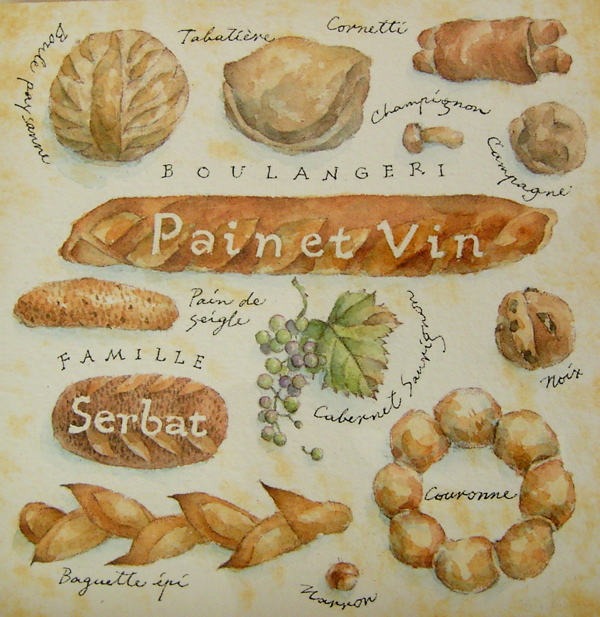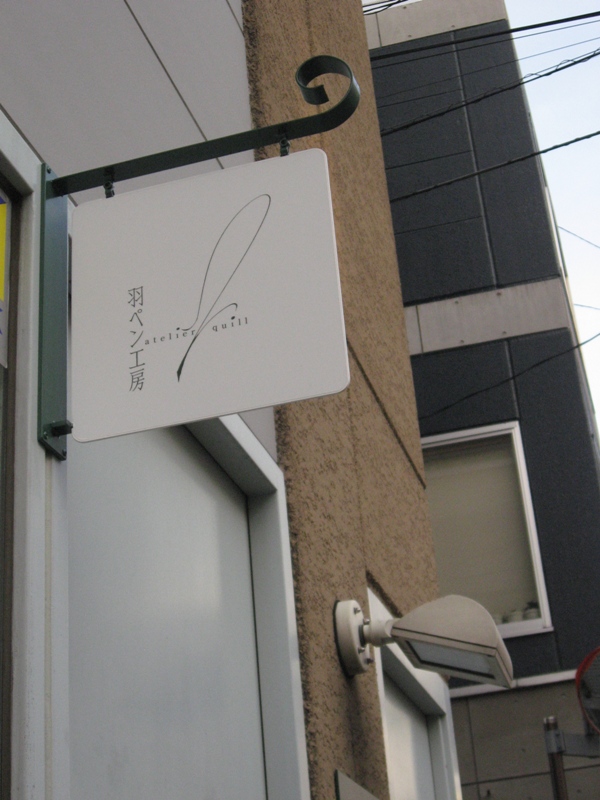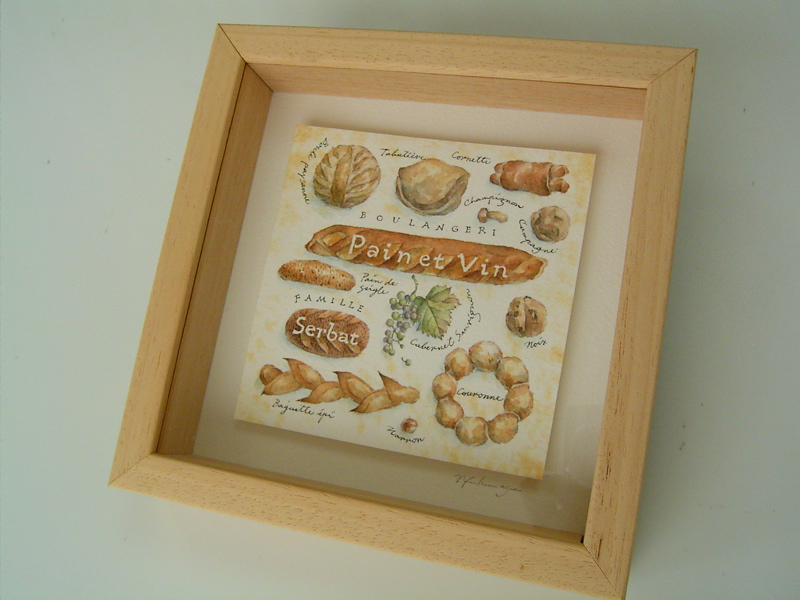
羽ペン工房について
この場をお借りして、少しばかり「羽ペン工房」のお話し…です。
mojitor-hは、ここでお店番をしたりします…。
ここは、羽ペンを削ることがメイン…羽ペンが象徴です。
その他、手で作るものを大切にしていきたい…そういう
ことが共有できる空間にしたいです。
カリ人さんには、カリ本も読める場にしたいです。
ギャラリーと工房を提供する空間です。
まだ、人手が足りないので、お店はちょっとしか開けません。
でも、羽工(人呼んで…)スタッフは頑張ります。
ギャラリーで使用していな時に工房とお店を兼ねて
オープンしています。…というか、今日初めてオープンしました。
オープンしている間は、お店番は何か作っていることでしょう…。今日そうしようとはりきって
行ったhですが、道具を一つ、しかも肝心要な道具を忘れてしまい…あらまぁ〜の一日でした。
まだ、本棚とか何も揃っていない
のですが…今日は、とても美しい
手書き、手作りのカードを並べました。これはJ-LAF http://j-laf.org/
が扱っているカリ人たちのカードです。秋・冬バージョンの新作ばかり
です。
来週は本棚が…。うれしい…。
(なので来週のメインは本棚組立?)
ドイツの印刷工房
ドイツのマインツにあるのが有名なグーテンベルグ・ミュージアム
です。
そして、そのお隣にまだまだ現役で活版印刷もしている
工房があります。
中にはおめめが「キャーキャー」していまうような道具がいっぱい!
古きものもたくさんあるので
しょうねぇ〜。
ここでは、いろんなWSも
やっているし、
イベントもあるみたいです。
時間が止まっているような
空間ですね。
2004年に行きました。
これらの画像はTさんのを
使わせて頂いてます。
私は、カメラが壊れてしまって、全然撮影できてません…(涙)
ここでは、試し印刷したものを購入もできます。
値段はあってないようなもの…だったような…。
ずいぶんお安く買え記憶があります。
私は、教会のようなグラフィックの図柄の
ものを買いました。
DRUCKLADEN と言います。
DRUCK(男性名詞)は、印刷という意味があります。
LADEN(男性名詞)は、お店という意味があります。
何か、LADENと言うとショップみたいな感じがしますが、
こういう使い方をするのですね…。勉強になるなぁ。
サイトからみると画像だけでも楽しめます…。Der Film uber uns をクリックすると
印刷の様子が見られますぅ〜。クリスマスのカードを自分で作ってますね!楽しそう!
五十音
前から行ってみたいと思っていました。
ちょっと訪れてみました。
不思議な場所にあります。
今や銀座は新しいショッピングゾーンに人、人、人・・・。
なのにここは大きな通り隙間?みたいな場所に
あるので、とっても静か・・・。
ちょっと異次元の空間に出現みたいな感じです。
ここは、ボールペンと鉛筆の専門店です。
デッドストックの筆記用具がたくさん・・・訪れる人を
待っています。
看板も可愛いです!
店内では、懐かしかったり、初めてだったり・・・とあまりに
楽しいので、時間が経つのも忘れてしまいました。
オーナーの方もとても親切で、つまない質問にも優しく答えてくれました。
私が購入したのは、鉛筆置きです。五十音のオリジナルですが、文字好きにもたまらない
デザインです。本の形で背には鉛筆の絵が!裏は「あいうえお・・・」なんですもの。
他にも「いろは・・・」とかありました。
ボールペンと鉛筆がたまらなく好きなお嬢さん・・・訪れてみてくださいね。癒されますよ!
アンティークフェア
さて、イギリスへ行ったら何と言ってもアンティークです。
ここは昨日ご紹介したDurhamの大聖堂の横にある大学の学生たちがディベートに使う講堂です。ここを夏休みの間だけけ使ってアンティークフェアが開かれています。
入場料がかかりましたが、そこでお宝グッズをたくさん発見!興奮状態!
最初入るかどうか迷った時に、ペンナイフはありますか?と聞いたところあるよとのことだったので行ってみると、ペンナイフ=小さな折りたたみ式ナイフでした。そうそう、そうだった。私たちが通常言ってるペンナイフは、クイルカッターと言わないと通じないのでした。そこでそう聞いてみると、はいあるよ、と出してくれたのがこの古いインク壷の前に置いたこれです。ちいさなバターナイフの様ですが、昔はこれで羽ペンを削っていたんですね。
古いインク壷たちも素晴らしいです。いろいろな形があるんですね〜〜。
こちらはふるーいインクです。このぼろぼろなのはウインザー&ニュートン。もう50年近く経っていますがまだ液体が少々残っていました。
そんなものがもうたっくさんあって、キャーキャー見つけるたびに大騒ぎです!
そして極めつけはこれ!
こんなの見たことありませんでした。
これはpounce pot(パウンスポット)と言って、粉を入れて振る道具です。パウンスとはガムサンダラックやパミスなどの粉の総称を言います。紙や羊皮紙にインクで書く時細くてきれいな線を出すために、ガムサンダラック、羊皮紙を書くための準備として表面の油分を取り、また表面に毛羽を立たせるためにはパミスを使います。それらをムラなくかけるための道具があったとは!・・・・・・。ひょ〜!
そしてこのまるっこいパウンスポットは、無事日本へお嫁入りしましたよー。(^∀^)/
でも、塩こしょう入れでも代用できそう。是非みなさんもお気に入りの容器でやってみては〜??
それにしても古い物は本当にいいね〜。
moji・・・?
何と今日は、カナダ特派員miko嬢からの報告です!
miko嬢は、7月下旬に行われたカナダでのカリコンファレンスに
参加していたのでありました。
なぜかmojitorという言葉に反応したとか・・・。それって、ねぇ・・・。
あれですよ・・・洗脳?(゚Д゚≡゚д゚)エッ!?
「mojito:」とな!
私も最初は、「mojitor」の飲物?
と驚きました〜。
惜しい〜でもいいですねぇ〜。
この、ちょっと外し感がたまりません!すっかりmojiさんは気に入ってしまいました!!
発音では「モヒート」と言うそうですが、ウィキペディアによればラムベースのカクテルの名前だそうです。mikoさん〜飲んだんですか?フフ。
お店の雰囲気もおしゃれですねぇ〜。こういう赤って好きですよね・・・あっちの人!
ボストンの大学もアリザリンクリムソンを使用してました。
だいたいにして、レンガとかの建物が多いから、
落ち着いた赤が似合うことは間違いなし!
景観にも厳しい規制をしてるし・・・。
あっ、そうそう、私達はモジトルです。
モヒトルではありませんよ!(゚∀゚)アヒャヒャ
紙のめぐみ
「紙のめぐみ」というその名の通り、ここへ行くととってもチャーミングでスウィートでピュアなめぐみさんお出迎えをしてくれます。
ここは静かで素敵でほっとする空間が保たれています。時間の許す限り、ずっ〜とここにいたい、という気持ちになるのです。
それは紙舗直の紙の風合いとめぐみさんのお人柄でしょう。
さてさて、神戸のH子さんからこの紙のめぐみに関して、お便りを頂きました。ご紹介します!『紙のめぐみで撮った写真を送ります。中は撮影できませんでしたが、112番の不思議なものだけ「撮ってもいいよ」と言われました。今は使っていないようですが、だるまストーブの煙突から出る煤をここから掻き出すのだそうです。○A三号(?)このアンティークなものにふたをせず、フレーミングするようにして和紙で貼っているところが、オーナーさんのセンスですね。建物の外観や床は、以前ギャラリーとして使われていたときのままだと言うことでした。
紙布(しふ)と言われてピンと来る人はあまりいないかもしれませんが、この柿渋染めバッグはその紙布でできています!縦糸か横糸のどちらかが、柿渋で染めた和紙を糸状のこよりにしたもので折られた「布」で作ってもらいました。紙のめぐみで同様のバッグを見せてもらい、その色や風合いが一目で気に入り、たすきがけで持ちたい&海外に持っていきたいということだけ伝えました。作ってくれるのはオーナーのめぐみさん。
そして2週間後に到着!たすき掛けするのに丁度良い長さとひもの幅。まちも蓋も内ポケットも付いています。そして何より「やられた〜」と思ったのが、後ろ側に付けてくれたポケットと、そのヘリの風合い。
反物の端っこって仕立てには普通使わないのかもしれないけど、紙が好きな人なら、こういうヘリって大好きですよね。その部分を使ってくれたのがとっても嬉しいし、めぐみさんならではだと思いました。オーダーメイドですが、とってもリーズナブルです。更に、色が薄くなってきたら直さんが上から染め直して下さるとか。
愛すべきグッズと共に海外に行ける幸せよ!そして、柿渋に魅せられている「柿渋女」が、さらに調子に乗ること間違いなし!』
ふふふ、H子さん、とても気に入ったバッグを作ってもらえて良かったですね!実物を早く拝見したいです
いつも感動していること
今日は画像がダンボール色で地味〜なんですが・・・いつも「すばらしい!」と感動していることなのでちょっと書きたくなりました。
ご存知、福永由美子さんに特注して作ってもらったのだそうです。
福永由美子
そのパン屋さんのお店の名前も入っています。
pain et vin つまり bread and wineということで、ぶどうの絵も入っていました。どのパンもフランスのおしゃれなパンです。あんぱんとか、カレーパンはないんです。じつに美味しそうでおしゃれなパンばかり。さすがフランスのパンです。
しかし、こんなに素敵なイラストと文字をオーダーして作ってもらえるなんて、良いことを聞きました。何でも書いて頂けるのかなぁ・・・。しかし、なんと福永さん曰く、パンを書いたのは初めてなのだそうですよ! いきなり書けるんですね、すごい!
福永さんは現在山梨で創作活動をしていらっしゃるので、この作品は山梨で生まれ、白山経由で九州の阿蘇へ旅立って行ったと言う訳です。
「ひきこもって仕事していても、作品は全国津々浦々で可愛がってもらえると思うと、報われます。」とおっしゃっていました。
もうこの作品は阿蘇のパン屋さんの壁にかけられているのでしょうか。きっといい匂いに包まれて、そのお店の繁盛をずっと見守っていくことでしょう。